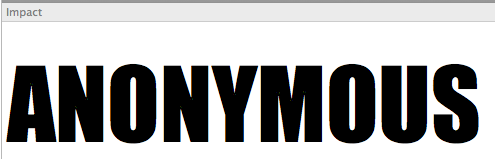
Schriftart gesucht
Die Impact scheint mir höher zu sein …
Wahrscheinlich haben sie Nimbus Sans verwendet …?
Edit: Bei der Impact fehlt auch die Serife am R …
Die Impact scheint mir höher zu sein …
Deswegen hatte ich »gequetscht« geschrieben. Aber die Nimbus scheint wirklich besser zu passen.
Das ganze Leben kostet, aber die Impact ist auf vielen Rechnern schon vorinstalliert, wenn Du die ein paar Prozent in die Breite ziehst, bist Du schon sehr nahe am Original.
Ich wollt mit der Schrift etwas arbeiten :)
Ich versuche es mal mit Impact und den paar %
Das mit den Prozent klappt leider nicht ganz. besonders beim E fällt es auf.